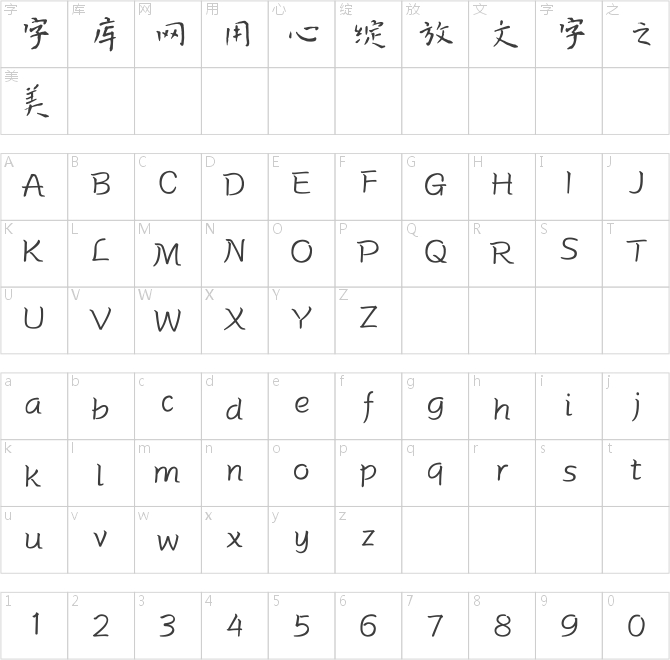
方正字迹-毛海飞古典楷书
方正字迹-毛海飞古典楷书介绍
今日生活之匆忙,灵魂跟不上生活节奏。追求内心质朴自然,平和,结构厚重而不浮,质朴而不板,深沉而不狂,点画不雕凿,不装巧,一任舒服浑然天成的感觉。
方正字迹-毛海飞古典楷书字体FZZJ-MaoHFGDKSJF简繁版字库是一款让人赏心悦目、百看不厌的中文字体,适合各类广告和产品包装设计应用,字体大小7.37MB,格式为TTF字体,上传用户是我,Dirac,作者/版权方为方正字库